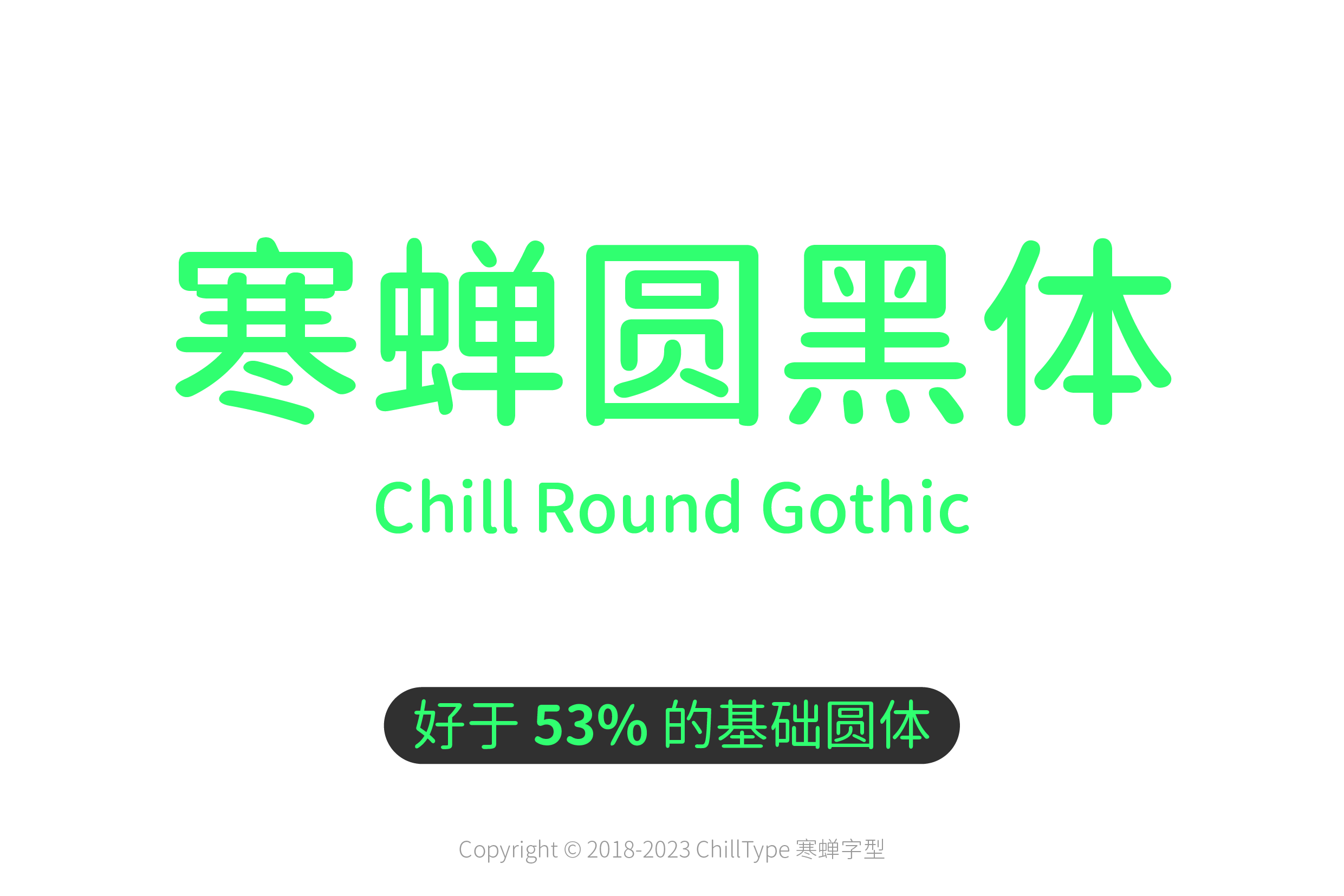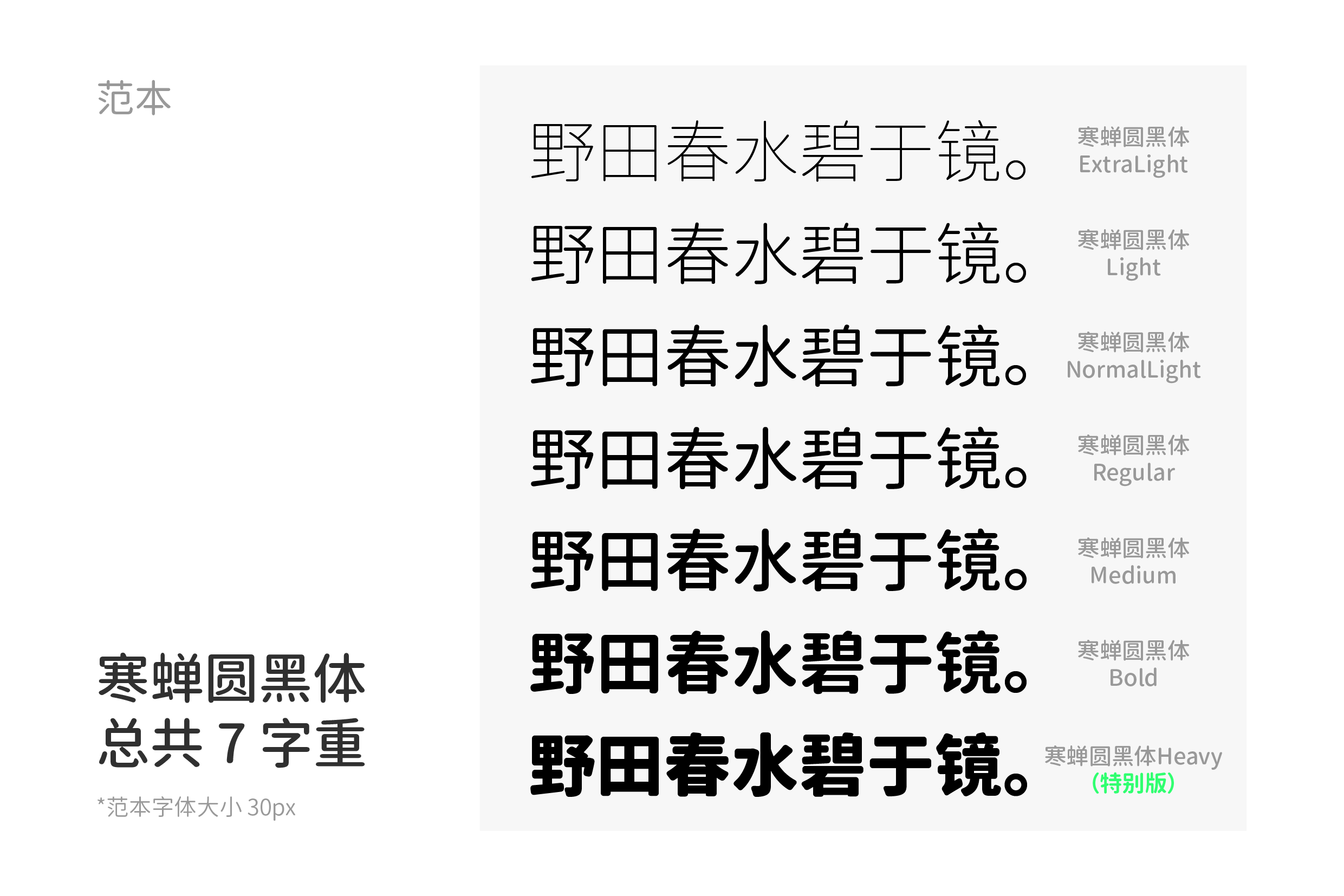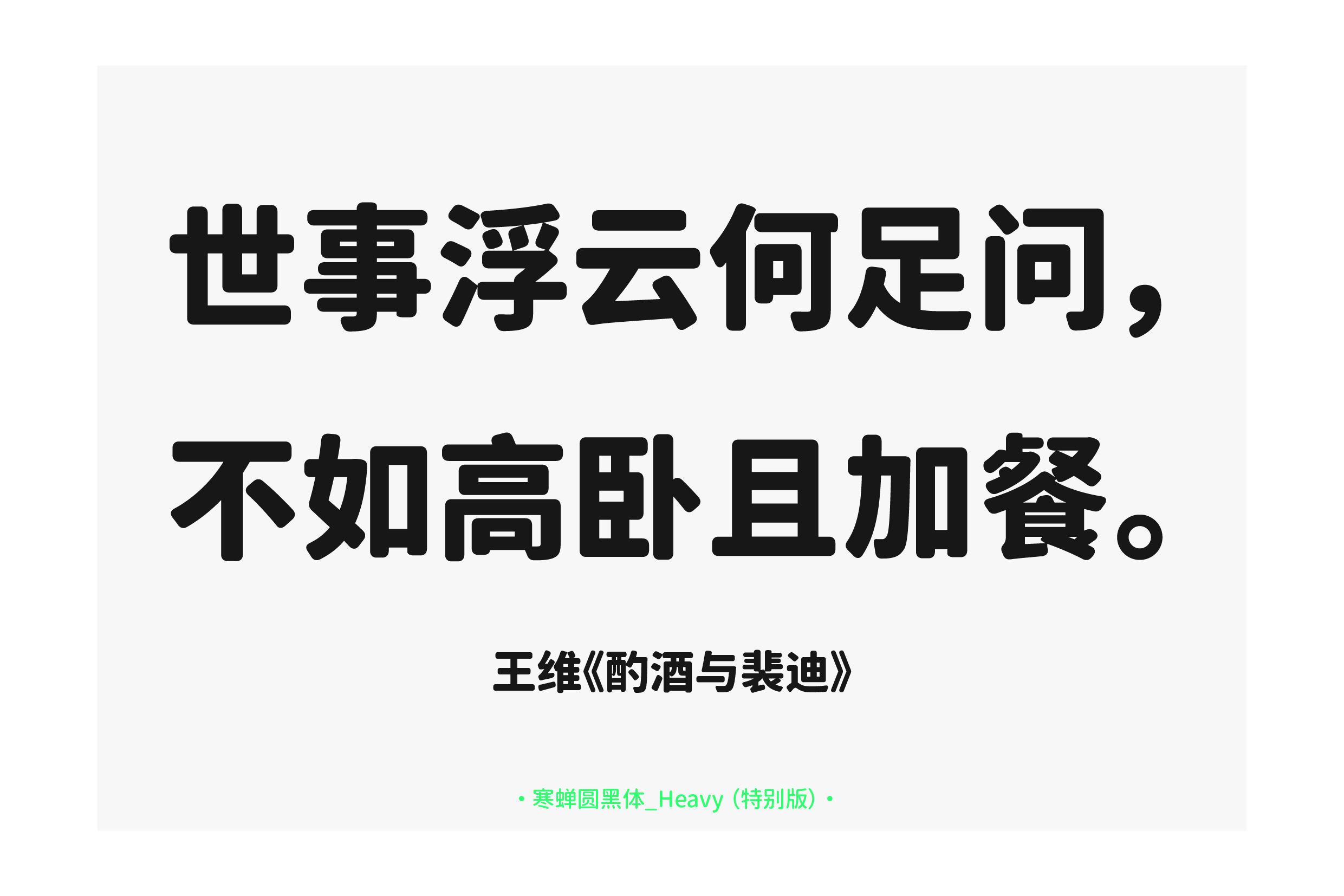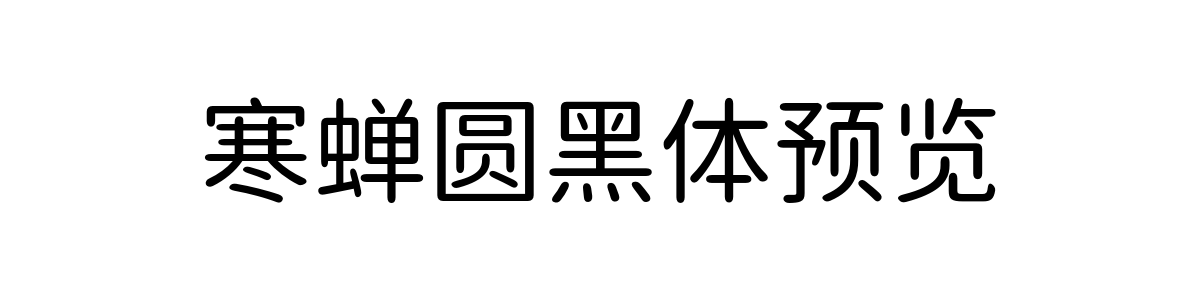
寒蝉圆黑体
寒蝉圆黑体(Chill Round Gothic)是一款通过算法对思源黑体进行精准圆角化转换,兼顾结构严谨与视觉亲和力的开源圆体。采用特定算法按比例对原字体的所有笔画转折处进行“原汁原味”的圆角化处理,未改变原有字形结构和笔画走势,从而在最大程度上保留了思源黑体均衡、可靠的骨架。
开发过程中,针对算法转换在 GB2312 字符集范围内可能产生的笔画粘连问题进行了手动校准与修复,确保了字符的清晰度。同时,对字体包进行了精简,删除了部分字形以优化文件体积。字体家族提供多个字重,其中“超粗”特别版本有意减小了圆角曲率,以保持笔画的力度感,仅作柔和化处理。
字体风格
寒蝉圆黑体与传统手绘设计的圆体不同,其圆角并非来自感性的描绘,而是通过精确、统一的数学规则从思源黑体的几何轮廓推导而来。这种生成方式使得圆角具有高度的一致性和机械美感,每个转折处的曲率都遵循着严密的逻辑。